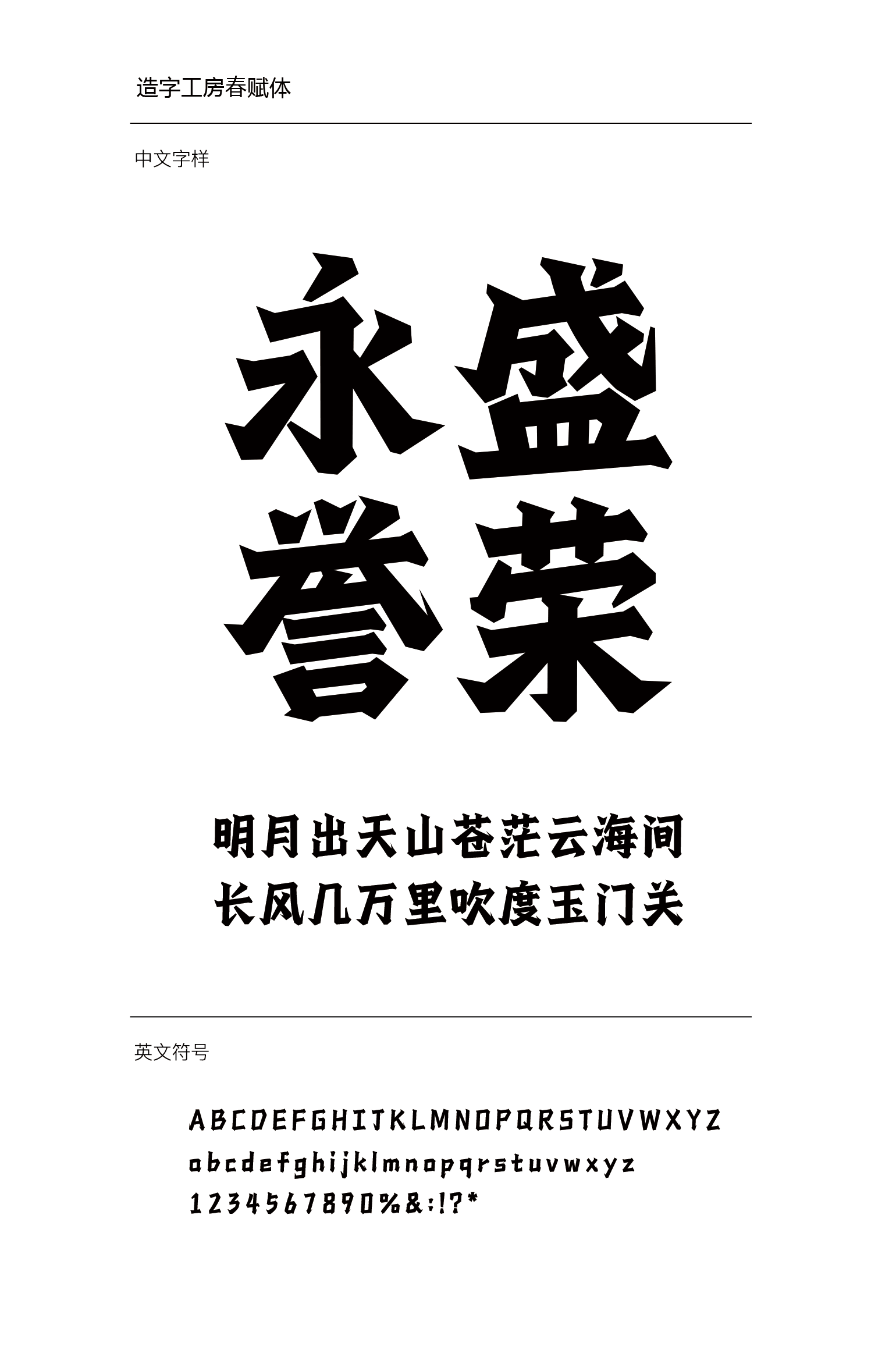
造字工房春赋
造字工房春赋设计说明
造字工房春赋体,整体感觉潇洒不拘束,笔触丰富,结构紧密,字形收放有度,笔画尖角自成风格,瘦劲清峻,结构遒美健秀,风神峻朗,笔画转折处简洁,线条充满韧劲,收笔停顿再回锋,尾端特点追求力量,体现潮流。点,提,钩的处理欲尖而锐,运笔灵活多变。设计师将传统书法融入现代设计语言,呈现一种独特的手工质感和文人气韵, 有极强的视觉表现力,适用于艺术作品,品牌设计,封面推广等环境。本字体为简体字库,采用OpenType/CID格式,Adobe-GB1-5编码。基于中华人民共和国GB2312-80字符集标准,另按需添加101个汉字。共收容字数6864CJK汉字,ASCII常用字符100个。